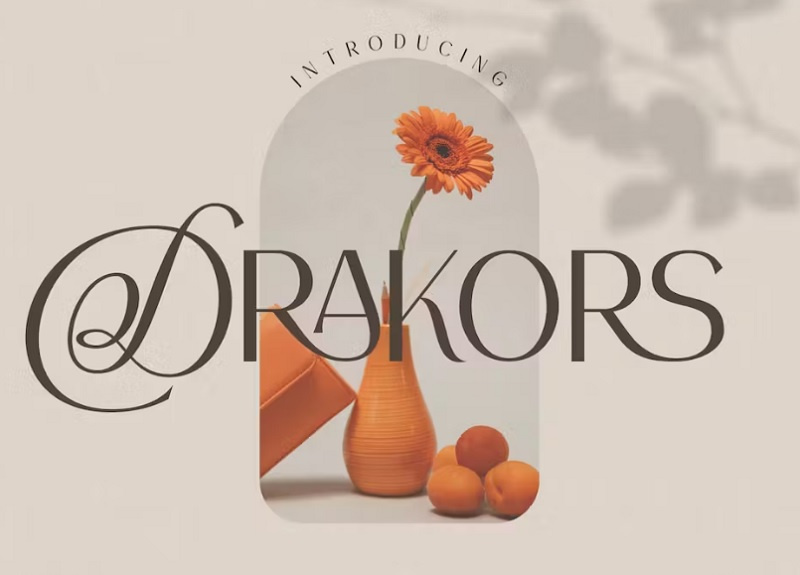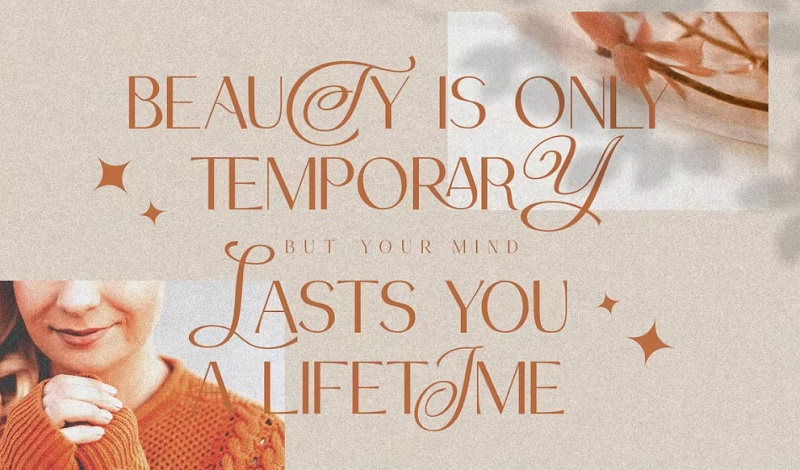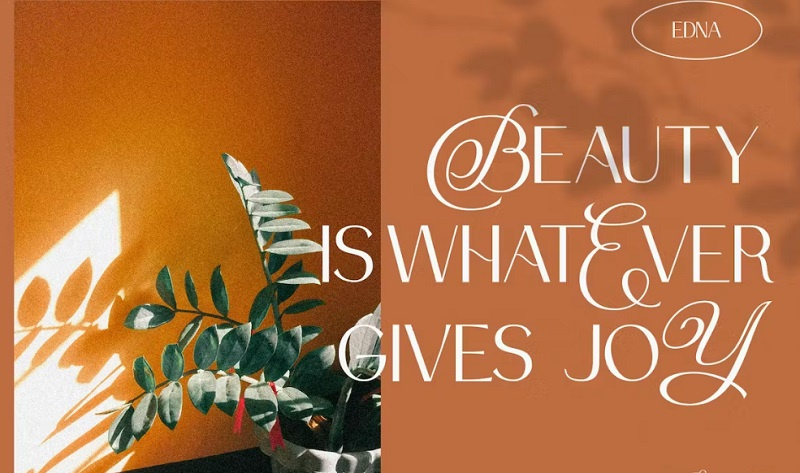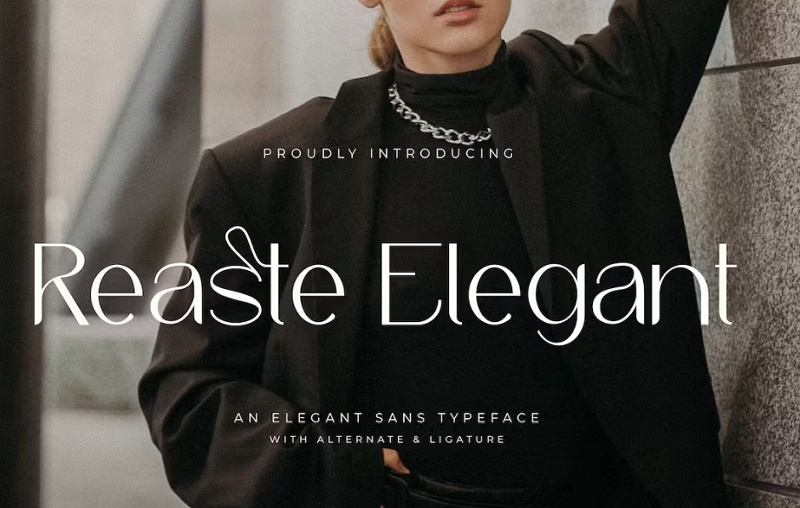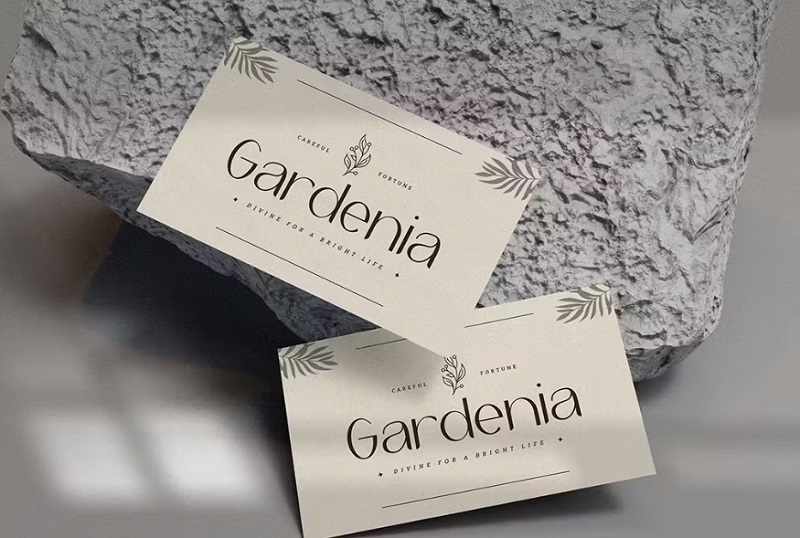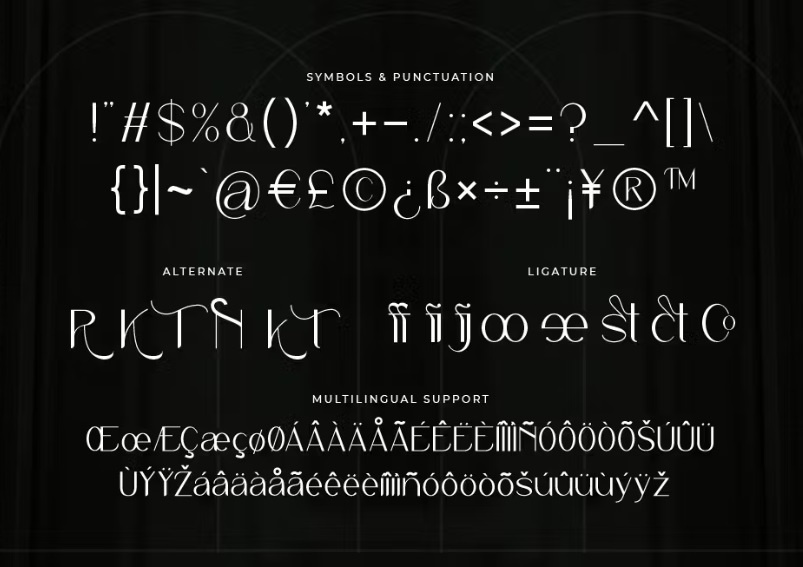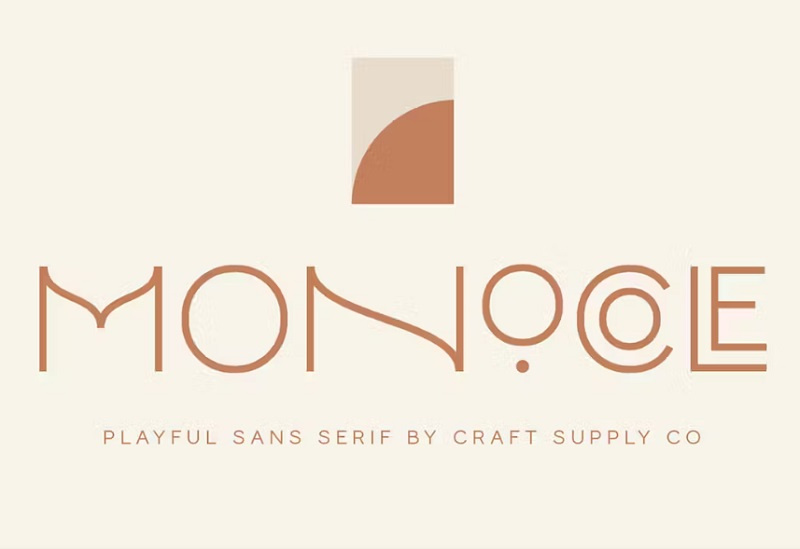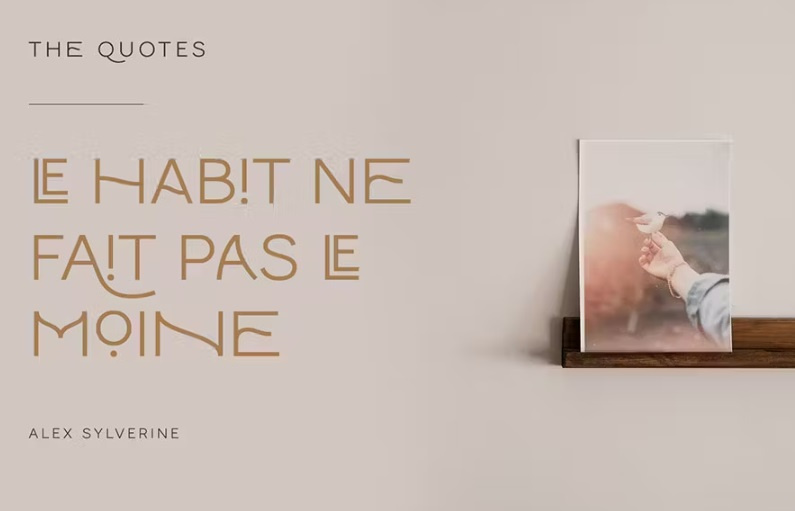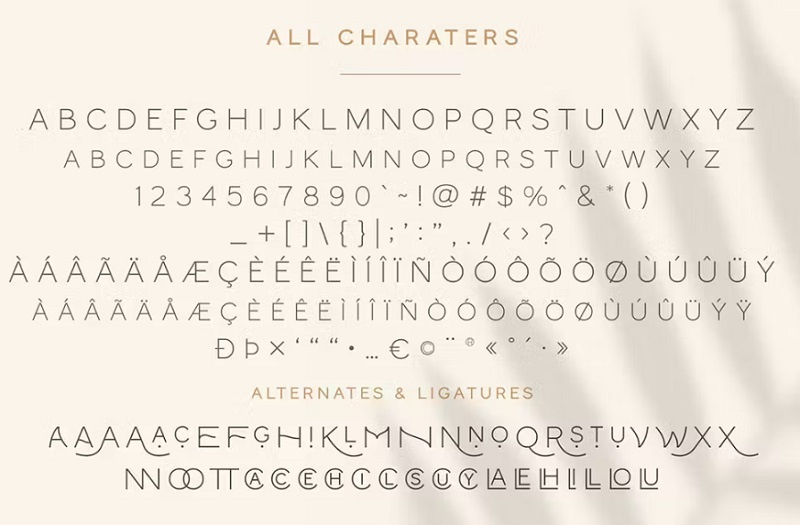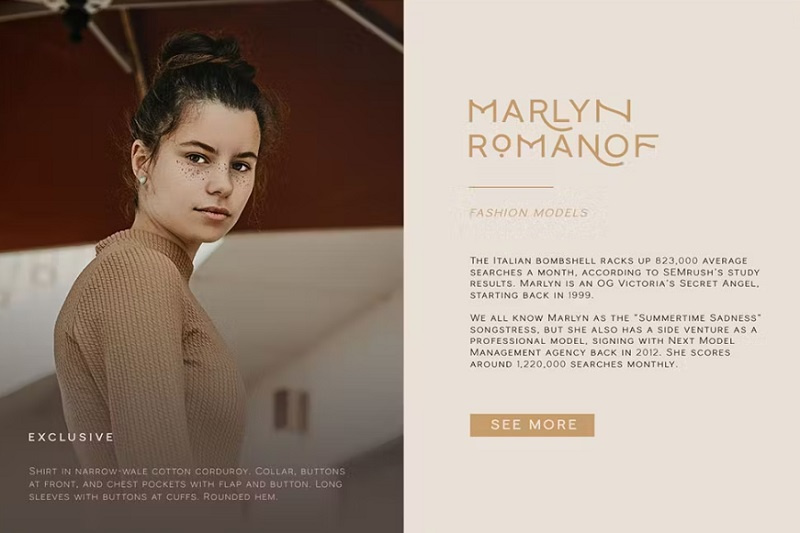
فونت ظریف انگلیسی که از سایت جی اف ایکس دانلود در اختیار شما کاربران عزیز قرار داده شده است شامل 3 فون زیبا و با سبک ظریف می باشد. یک فونت منحصر به فرد و نمایشگر مدرن برای نیازهای برندسازی ظریف و درجه یک. با فونت انگلیسی ظریف طراحی های خود را شیک تر و مدرن تر نشان دهد.
1- دانلود فونت ظریف انگلیسی Callge
این فونت ظریف انگلیسی Callge خطی است که از حروف انگلیسی دست نویس الهام گرفته شده است که می توانید در طراحی لوگوتایپ ، نشان تجاری، پوستر و غیره از این فونت زیبا و ظریف استفاده کنید.
2- 2 فونت انگلیسی ظریف
این مجموعه مناسب طراحان وب سایت و گرافیست ها برای پروژه های تبلیغاتی و تجاری می باشد. فونت انگلیسی ظریف شامل 2 فونت زیبا است که به راحتی می توانید آن را نصب و استفاده نمایید.
3- فونت انگلیسی ظریف و زیبا Monocole
فونت انگلیسی ظریف و زیبا Monocole مناسب برای استفاده در طرح و پروژههای گرافیکی مختلف از جمله طراحی پوستر، بروشور، لوگو، کارت ویزیت می باشد. این فونت ظریف شامل تمام حروف بزرگ، اعداد و علائم نگارشی و نویسه های چند زبانه می باشد.
4- دانلود فونت ظریف انگلیسی Delicate
Delicate یکی دیگر از سری فونتهای ظریف و باریک انگلیسی است. فونتی ظریف، لاکچری و جذاب که خلاقیت و زیبایی خاصی به طراحیهای شما میدهد. برای دانلود فونت ظریف انگلیسی و مشاهده پیش نمایش آن در ادامه مطلب با ما همراه باشید.